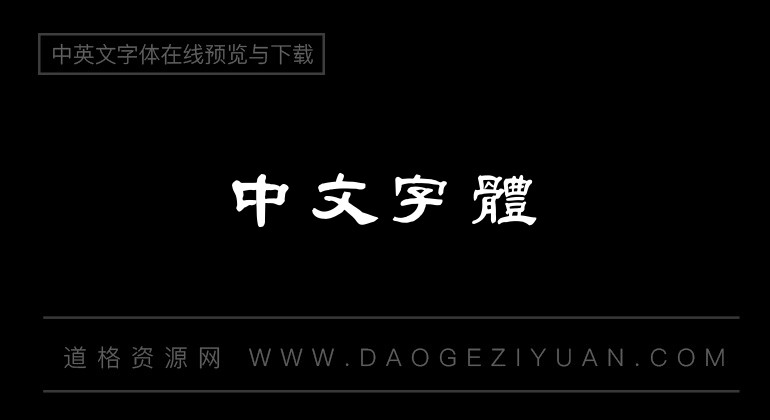
汉鼎繁特隶
汉鼎繁特隶是一款中文字体,由汉鼎字体设计师杨洪宇先生设计,于2015年发布。汉鼎繁特隶字体以汉鼎繁体为基础,并结合集汉字经典繁体特色,加入了新的字形,以及更加精细的笔画,使字体更加笔直,更加富有节奏感,更加细腻,更加优雅,更加具有艺术感,更加易读。汉鼎繁特隶字体可以用于印刷出版,书籍装帧,广告设计,网页设计,电脑桌面等,是一款非常适用的中文字体。
汉鼎繁特隶是一款非常不错的手写艺术字体,具有很好的视觉感,适合于文化类的宣传设计、商业类品牌的广告和产品包装设计以及个性化文字排版等较多场景。